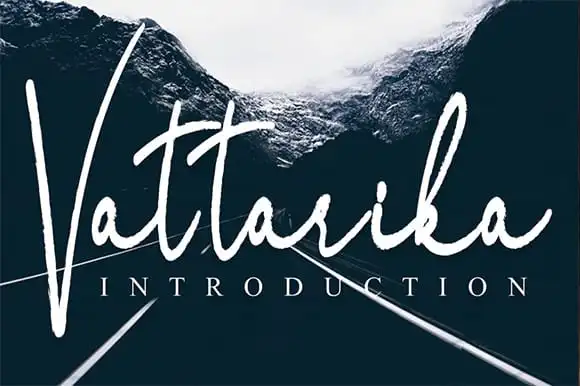
Vattarika Script Font – Download Grátis
Descubra a Vattarika Script Font, uma fonte Brush ideal para criadores de conteúdo digitais. Esta elegante e versátil fonte está perfeitamente adaptada para diversos projetos, incluindo desenhos na parede, invitations de casamento ou aniversário, logos para posts nas redes sociais, embalagens de produtos, rótulos, fotos e até mesmo logotipos de marca. Seja qual for o seu projeto que exige um toque delicado de escrita a mão, esta fonte é certamente uma escolha excelente. E para quem está procurando por uma fonte Brush perfeita para personalizar invitations ou material de escritório, a Vattarika Script Font tem algo especial para oferecer. Aproveite e deixe seu trabalho brilhar com a graça da Vattarika Script Font.